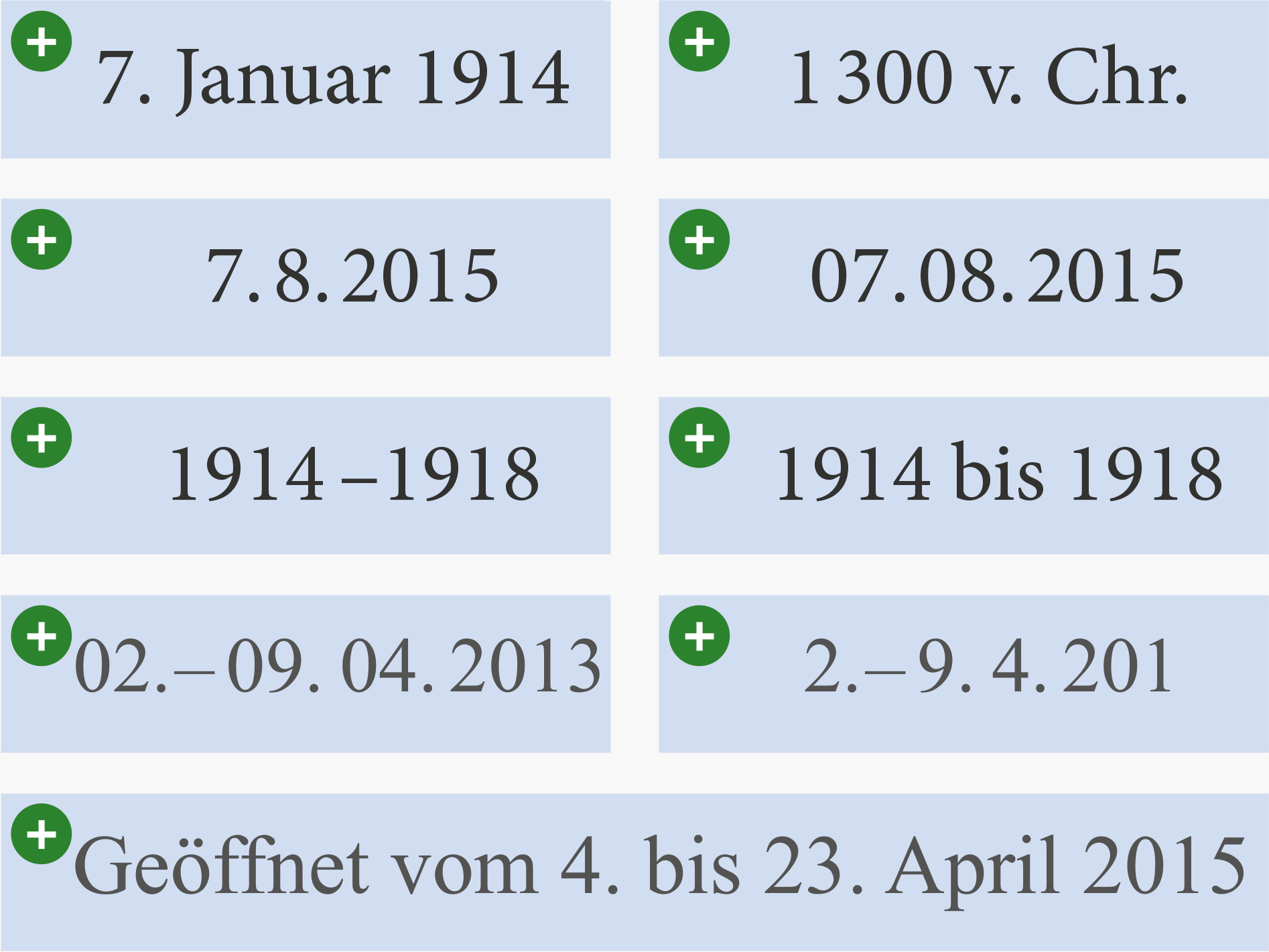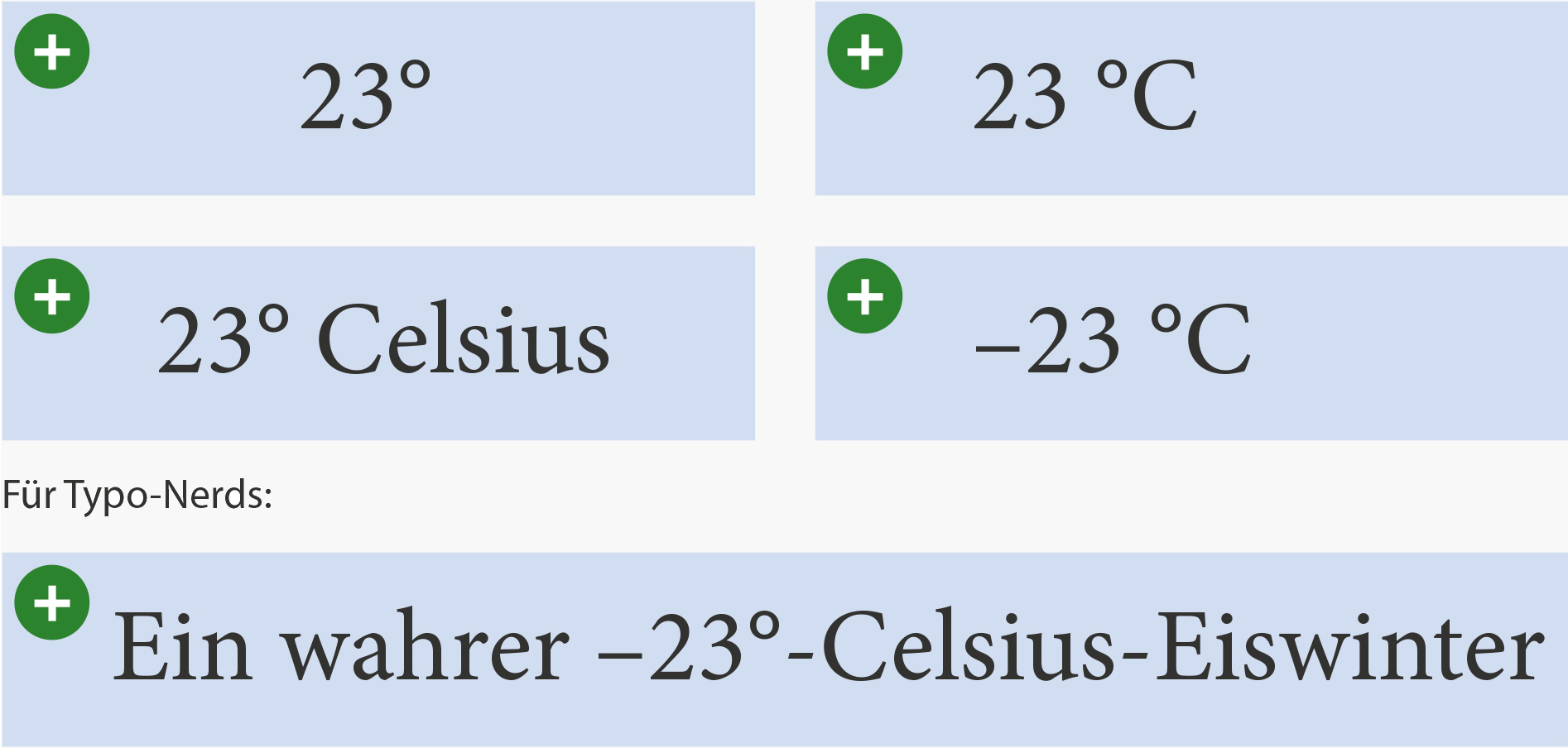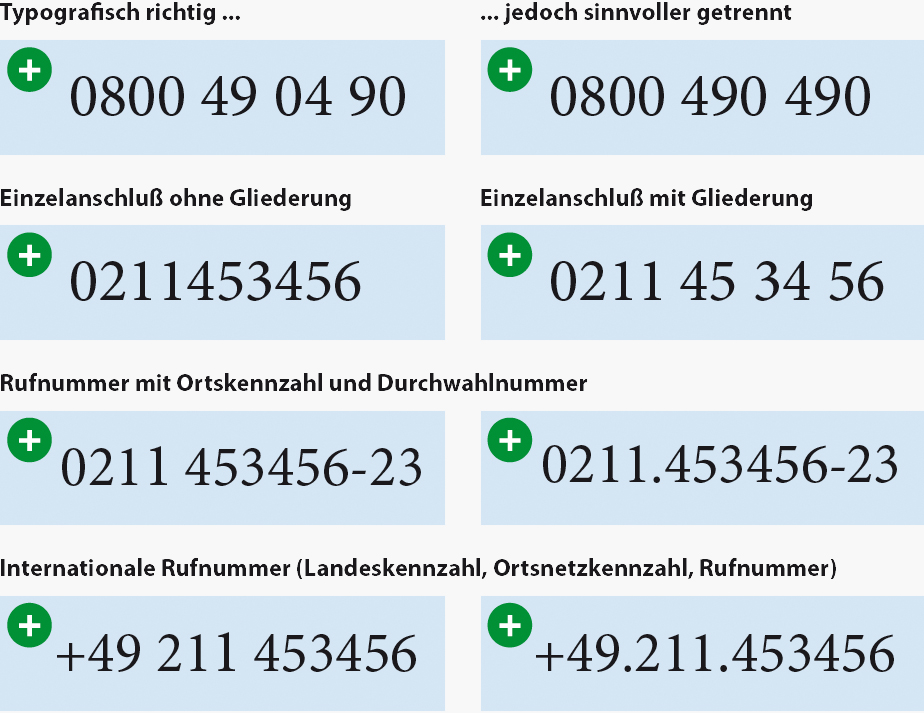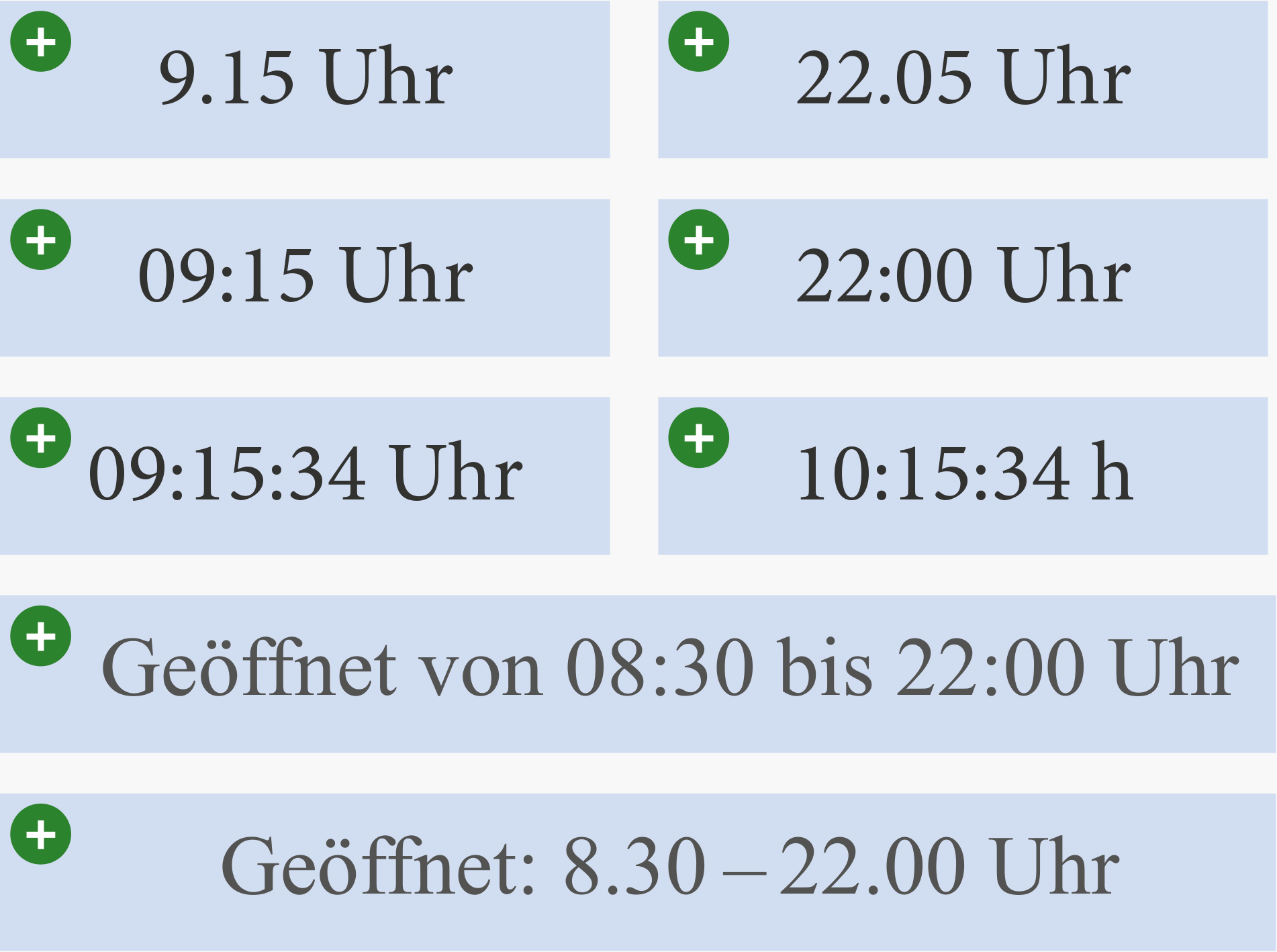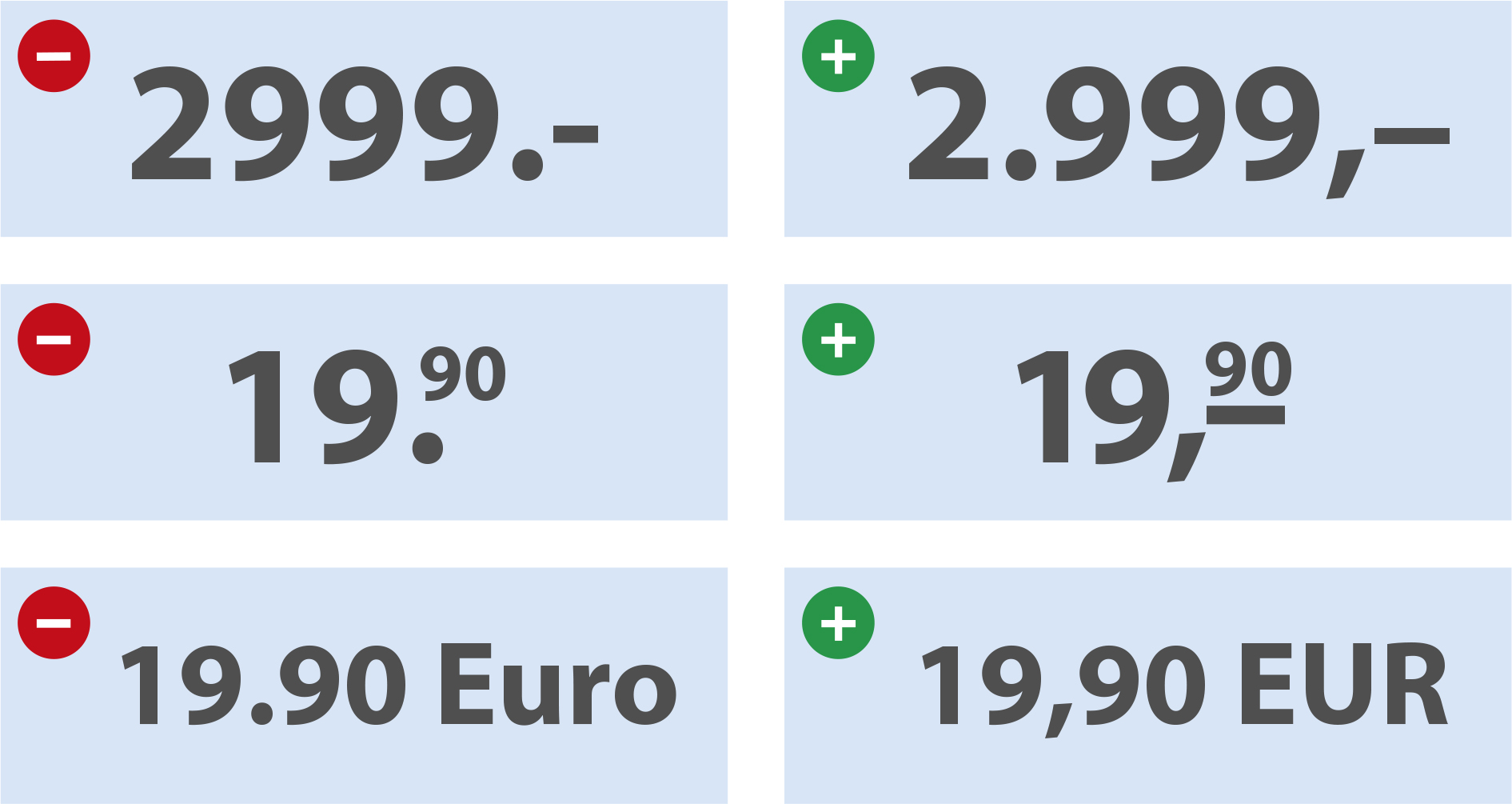
Preisverdächtig: Schreibweisen von Zahlen in der Typografie
Wie sagt Erik Spiekermann immer? „Typografie macht Spaß!“ Damit hat er natürlich Recht. Das bedeutet aber nicht, dass Typografie auch immer einfach ist. Ganz im Gegenteil, wie das oben stehende Angebot beweist. Ich habe es vor einiger Zeit in einem Laden in Düsseldorf-Bilk entdeckt (ich konnte leider kein Foto schießen, deshalb hier nur ein ungefährer Nachbau). Zwar glaube ich fest daran, dass jeder versteht, was der Ladenbesitzer zum Ausdruck bringen wollte. Trotzdem bin ich der Meinung: Es geht auch richtig. Deshalb möchte ich an dieser Stelle einige Anregungen geben, wie man mit Zahlen in der Typografiepraxis vielleicht besser umgehen kann.
Schreibweisen von Zahlen in der Preisauszeichnung
Nicht mit jeder Schreibweise erreicht man sein (typografisch korrektes) Ziel. Hier ein paar Beispiele für richtige und falsche Preise, die uns im Alltag häufig begegnen:
Schreibweise von Preisen in Der Typografie mit InDesign
Zahlen in der Lesetypografie
Zahlen im Lesetext nehmen immer störenden Einfluss auf die Lesbarkeit. Deshalb empfehle ich neben der Verwendung von Proportionalziffern anstelle der standardmäßigen Tabellenziffern folgende sinnvolle Maßnahmen:
Ziffern stören im Allgemeinen den Lesefluss. Zahlenangaben von null bis zwölf werden ausgeschrieben, ab 13 werden Ziffern verwendet. Deshalb setzt man in aller Regel: das zwölfte Jahrhundert oder im fünften Stockwerk. Ausnahmen werden zu Gunsten der Übersichtlichkeit gemacht: So werden aus 10 Fünfundsechzigcent-Briefmarken besser zehn 65-Cent-Briefmarken.
Anders verhält es sich bei Ziffernangaben mit Maßeinheiten: 8,7 hl. oder 6 m Baudraht. Übersichtliche und verständliche Kommunikation hat Vorrang, deshalb: Wir benötigen 9 Mitarbeiter, 5 Fahrzeuge und 5 Laptops, um die Außendiensttätigkeit in Zukunft weiter auszubauen … Nicht: 32,00 Euro oder 32,- Eur sondern 32 EUR. Zwischen Euro und Cent wird ein Komma gesetzt: 34,20 EUR.
Lange Zahlenangaben mit Wertangaben wie 3.456.320 EUR werden mit Punkt gesetzt. Alle anderen Zahlen erhalten Leerzeichen: 34 470 Flüchtlinge sind eingewandert …
Schreibweisen von Telefonnummern
Hier sind mittlerweile viele Varianten möglich. Ich persönlich entscheide mich immer für eine sinnvolle Trennungen, weil die Schreibweisen von Zahlen in der Kommunikation die Eigenschaft haben sollen, sich leicht merken zu lassen. Telefonzahlen können anstelle eines Leerzeichens besser mit einem Viertel- oder Sechstelgeviert getrennt werden.
Schreibweisen von Telefonnummern in der Typografie mit InDesign
Schreibweisen von Postfächern, Postleitzahlen und internationalen Postleitzahlen
Postfächer werden in Zweiergruppen von hinten getrennt und ohne ein führende 0 gesetzt:
Postfach 4 56 78
Postleitzahlen werden stets zusammengeschrieben:
40215 Essen
Internationale Postleitzahlen erhalten eine ausgeschriebene Landeskennzeichnung in einer neuen Zeile:
40215 Essen
Deutschland
Schreibweisen von IBAN und BIC
Schreibweisen von Geldbeträgen und Zahlenmengen
In beiden Fällen werden mit Punkt und Komma bzw. Leerzeichen drei Stellen von rechts nach links abgetrennt:
Bei Geldbeträgen: 3.335.667,72 EUR
Bei Zahlenmengen: 3 335 667 Tablet-Apps
Schreibweisen von Hausnummern
Zusammengefasste Hausnummern werden mit einem Gedankenstrich (langer Strich) ohne Leerzeichen versehen:
Graf-Adolf-Allee 248254
Schreibweisen von Zeitangaben
Verschiedene Schreibweisen – besonders geprägt durch die digitale Zeitangabe – sind möglich. Ein Gedankenstrich und ein Achtelgeviert ersetzen das Wort „bis“ (siehe dazu auch mein Blogthema: Auf den Strich gekommen: Typografische Striche richtig einsetzen).
Schreibweisen von Zeitangaben in der Typografie mit InDesign
Datumsangaben
Bei Datumsangeben kann nach dem Punkt anstelle eines Leerzeichens auch ein Achtelgeviert verwendet werden:
Schreibweisen für Datumsangaben in der Typografie mit InDesign
Ordinalzeichen, Gradzahlen
Der Höhepunkt typografischen Schaffens ist die richtige Schreibweise von Gradzahlen in Verbindung mit der Maßeinheit Celsius. Zugegeben, ich muss es selber immer wieder nachschlagen.
Schreibweisen von Gradzahlen in der Typografie mit InDesign
Weitere Schreibweisen in der Typografie